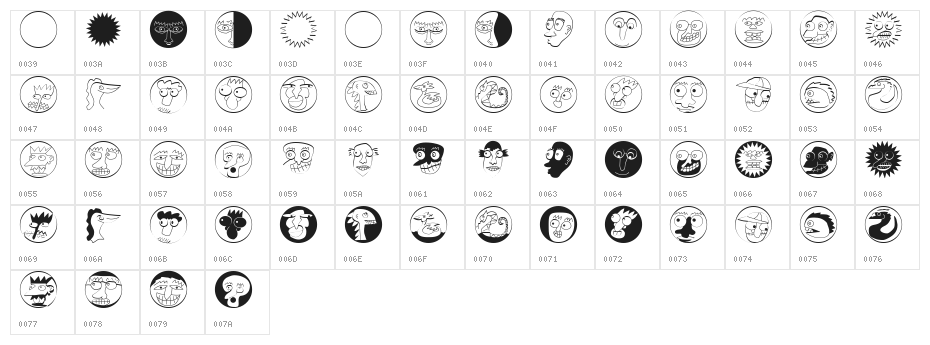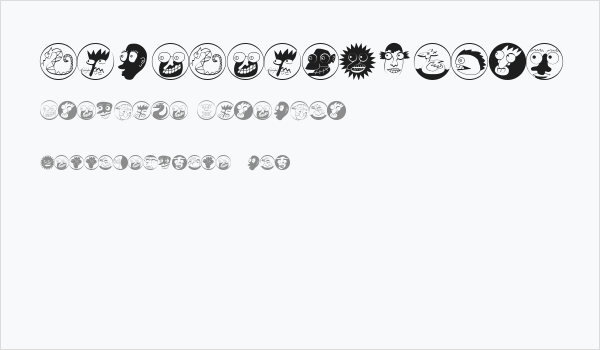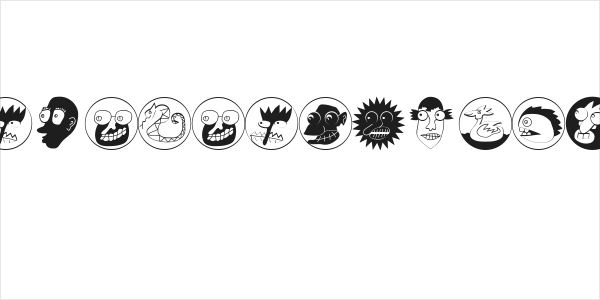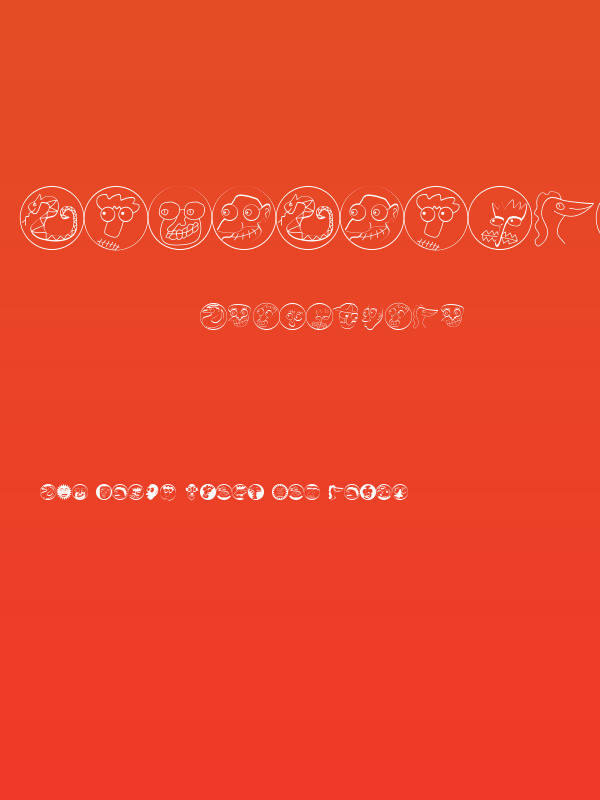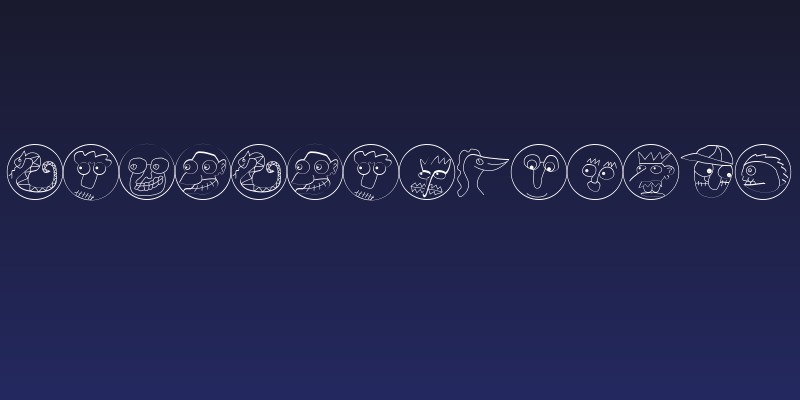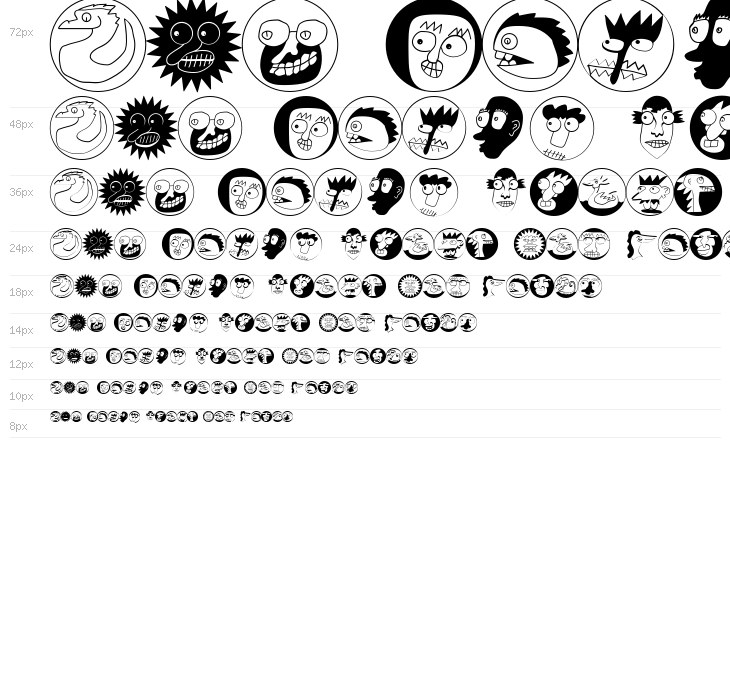
NiceNeighbours Font
| Stile generale | Cartoonish, Fun, Whimsical |
| Caso d'uso | Logos, Posters, Invitations |
| Progetti proposti | Ideal for children's books, comic strips, playful branding, party invitations, and any project requiring a fun and whimsical touch. |